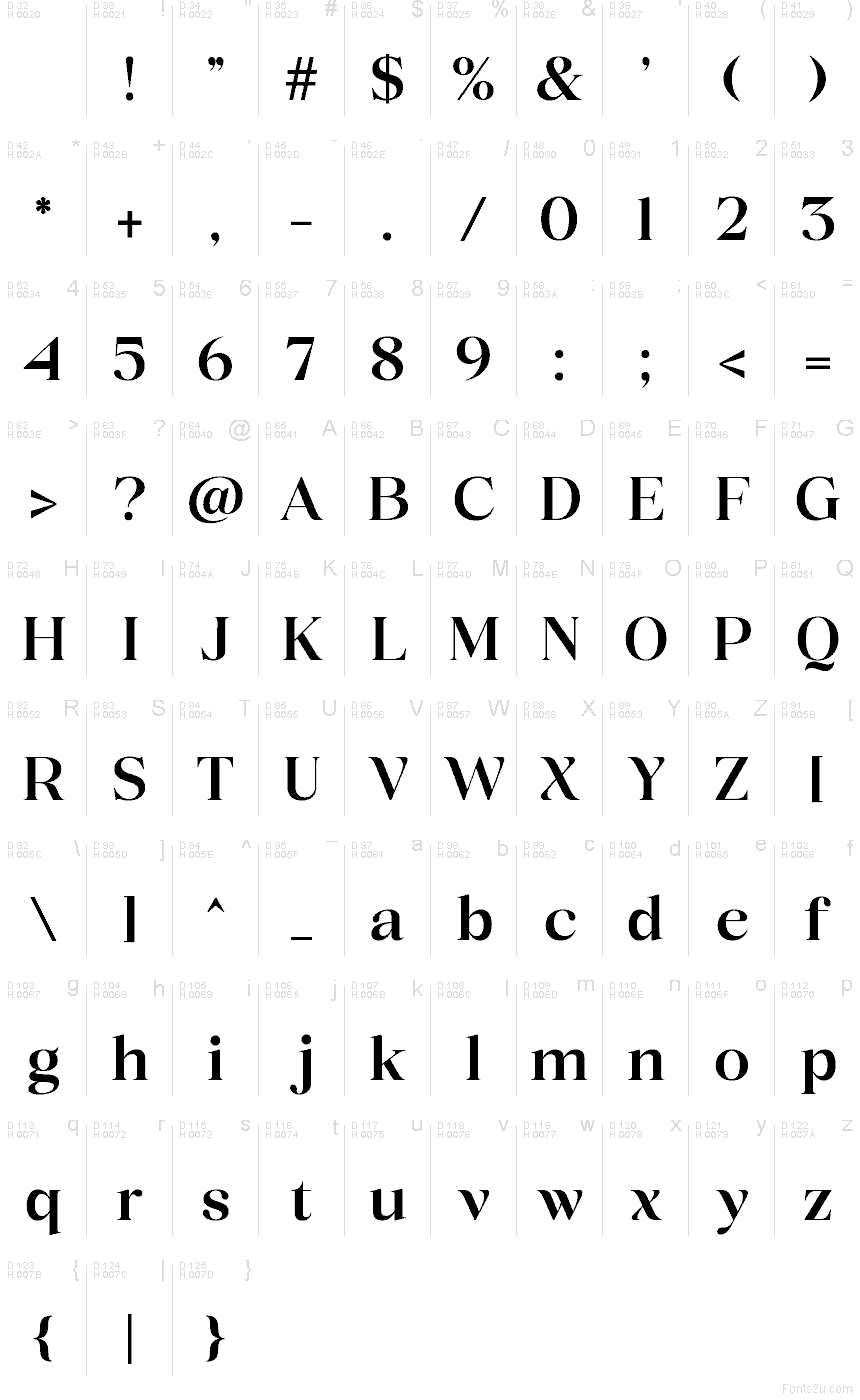
Scaver Medium von Glyphminds Studios ist eine kostenlose, kontrastreiche Serifenschrift mit einer ausgeprägt redaktionellen, leicht kalligrafischen Note. Die Buchstaben verbinden weite, geschwungene Kurven mit scharfen, zulaufenden Spitzen, wodurch die Schrift elegant und dramatisch wirkt, ohne ihren flüssigen, klassischen Rhythmus zu verlieren.
Sie passt perfekt zu Fashion-Magazintiteln, Buchtiteln, Plakaten, Verpackungsdesigns und Branding für die Gastronomie – besonders dort, wo es nicht auf wuchtige Wirkung, sondern auf Anmut ankommt. Als kostenlose Schrift eignet sie sich auch hervorragend für raffinierte Monogramme, Titelkarten und Initialen, da die ausgeprägten Kurven und zulaufenden Serifen selbst wenigen Buchstaben eine wohlüberlegte, komponierte Präsenz verleihen.